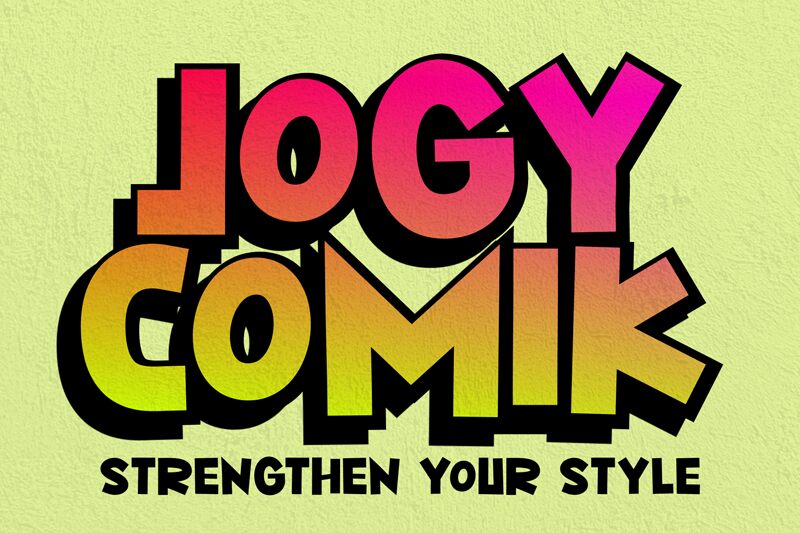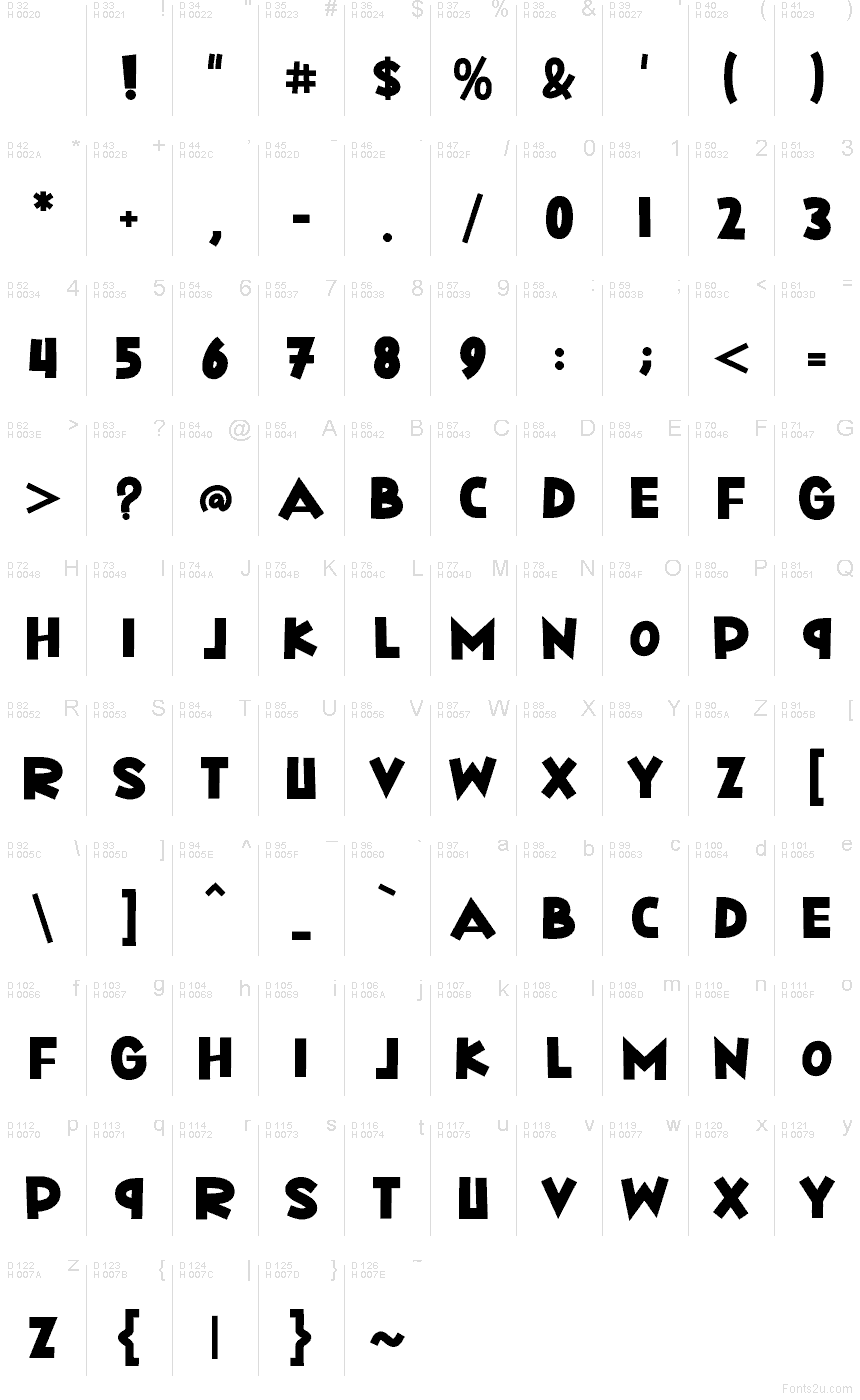
Jogy Comik, criada pelo Mabhal Studio, é uma fonte display gratuita estilo banda desenhada, com letras maiúsculas grandes e robustas que têm um movimento divertido de cartoon. As letras parecem recortadas a partir de formas ousadas, em vez de desenhadas com geometria rígida, misturando contornos arredondados com ângulos ligeiramente inclinados que conferem a esta fonte uma voz descontraída e alegre.
É perfeita para posters, marcas infantis, embalagens de snacks, miniaturas de YouTube e títulos estilo banda desenhada onde palavras curtas precisam de um impacto direto e positivo. Como é uma fonte gratuita, funciona muito bem para fanzines, autocolantes e capas, especialmente quando quer letras maiúsculas que sejam amigáveis, mas com peso suficiente para segurar o layout.